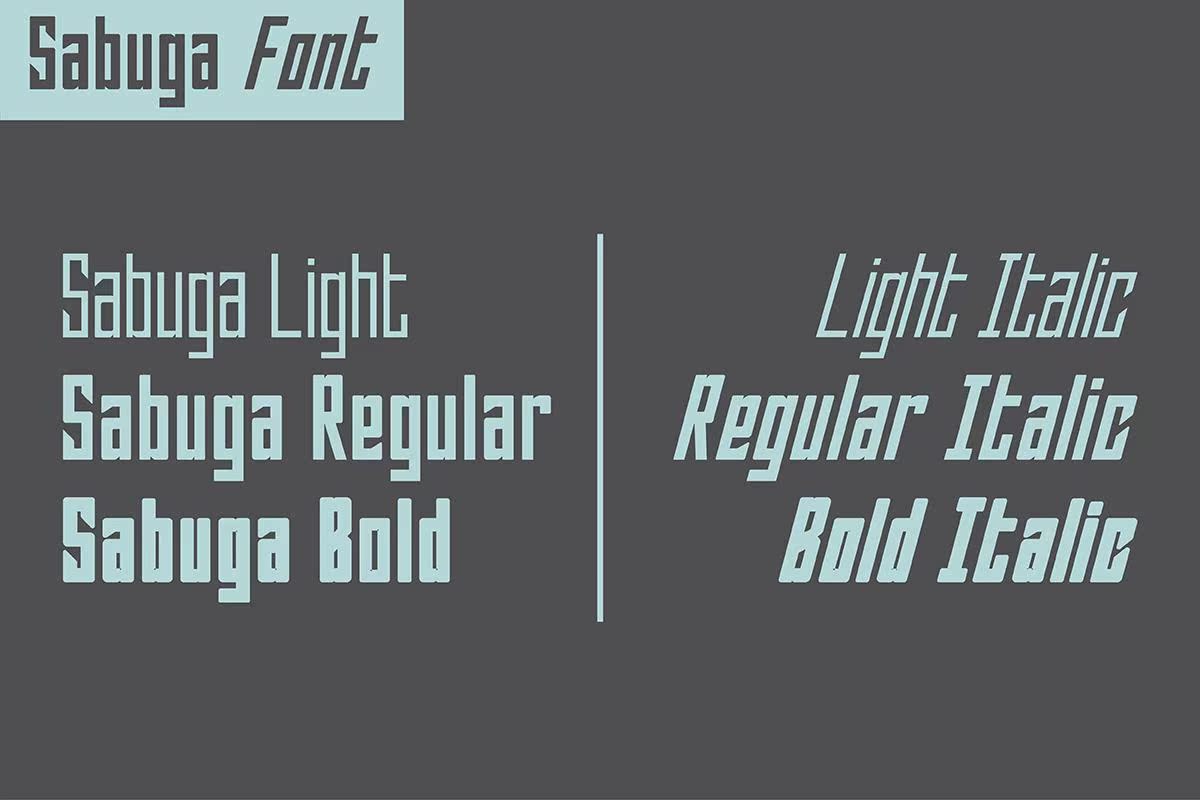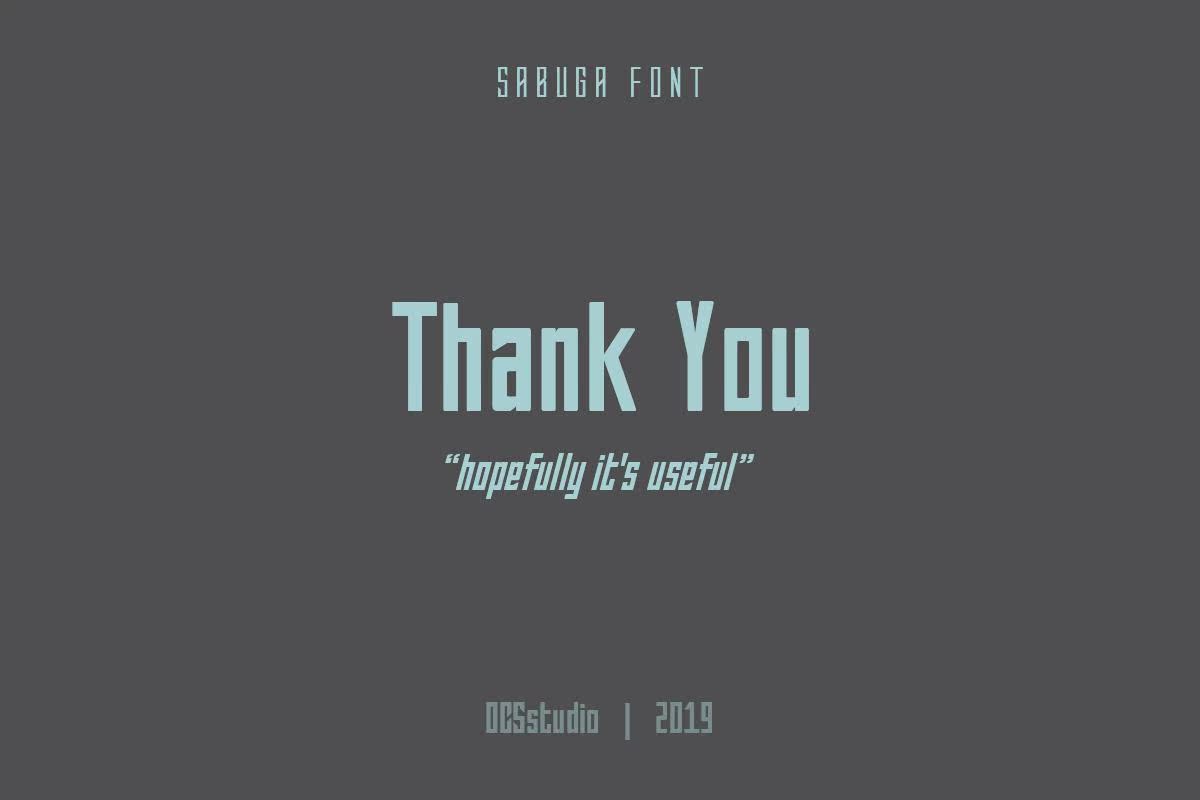
SabugafontNormal于2019年由Yocs Studios创建。该Fonts是一款经过充分起草和清洁的现代NSSERVICE产品。SabugafontNormal可用于设计模板、活动、邀请函、护送卡、表号、报价、展示、徽标、博客幻灯片、特色服饰、邮票、包装、贺卡、网站等。SabugafontNormal,是由YocsStudio2019年创建的。该字体是经过精心设计和清洁的现代NSSERVICE字体。该字体适用于设计模板、活动、邀请、护送卡、表号、报价、显示、徽标、博客幻灯片、特色服饰、邮票、包装、问候卡、网站等